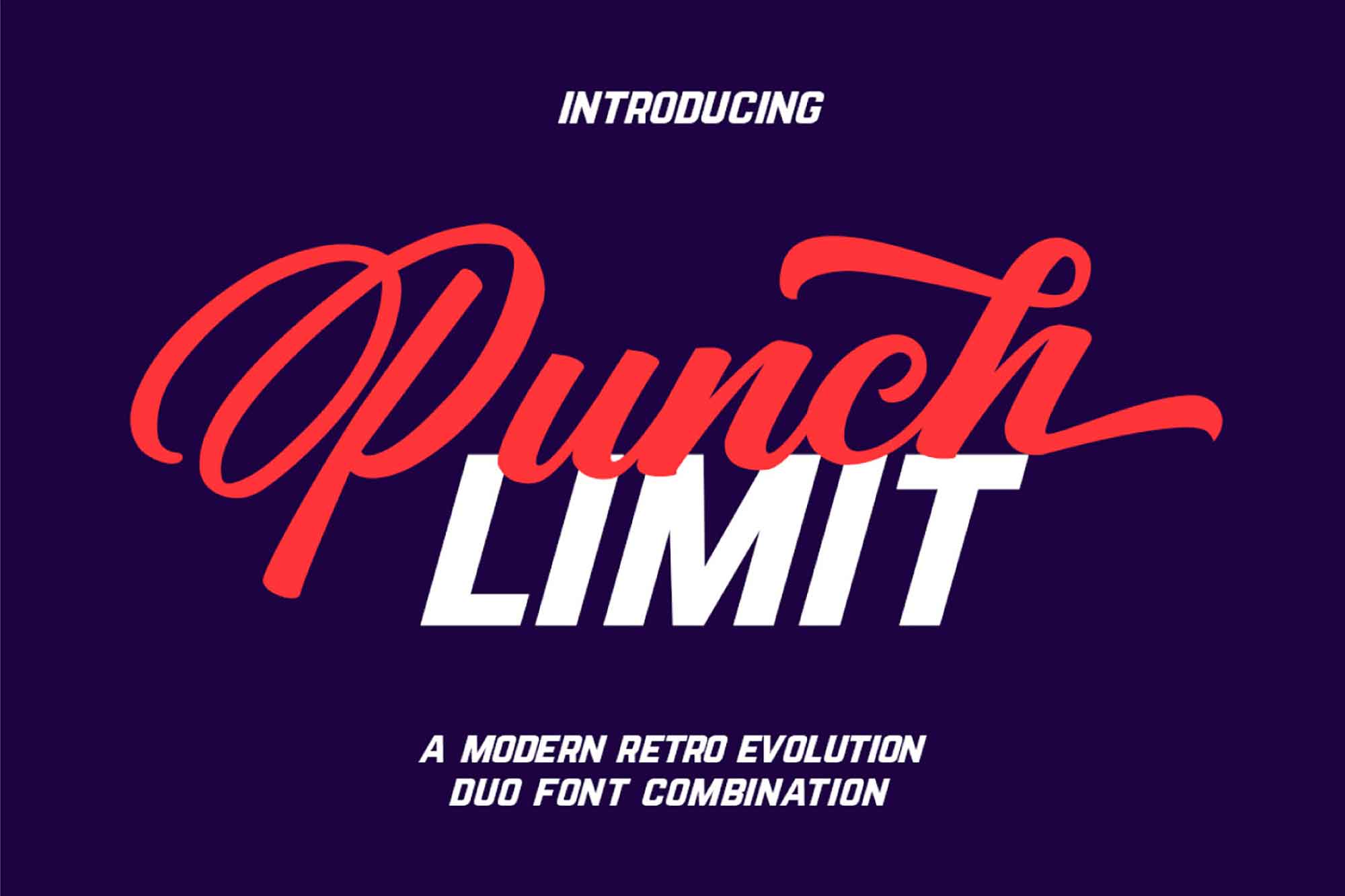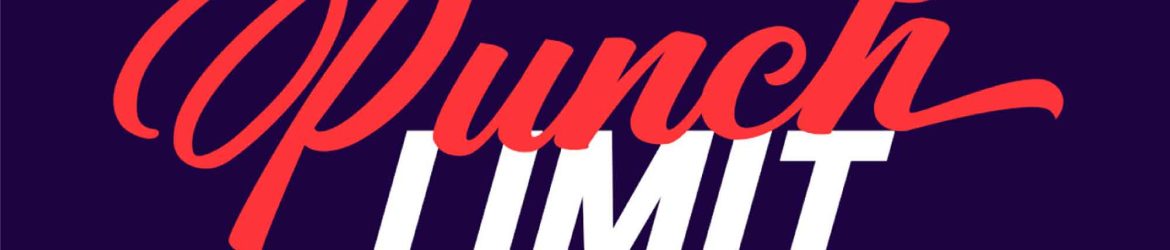
Punch Limit Script Font – Download Grátis
A novidade que estamos apresentando é o Punch Limit, um novo adição à família de fontes de tipos. Quem diria que a criatividade tem um limite? Não, claro que não! Com sua seleção extensa e opções alternativas, o Punch Limit está aqui para garantir que suas criações estejam livres de qualquer restrição. É uma fonte de tipos perfeita para aqueles que buscam criar designs sem limitações, sejam eles em design gráfico, publicidade ou qualquer outro campo do design. O Punch Limit é o segredo que você precisa para transformar sua visão criativa em realidade, sem preocupações sobre o que é ou não possível. Tente ele agora e descubra como a liberdade criativa se expressa em cada letra.